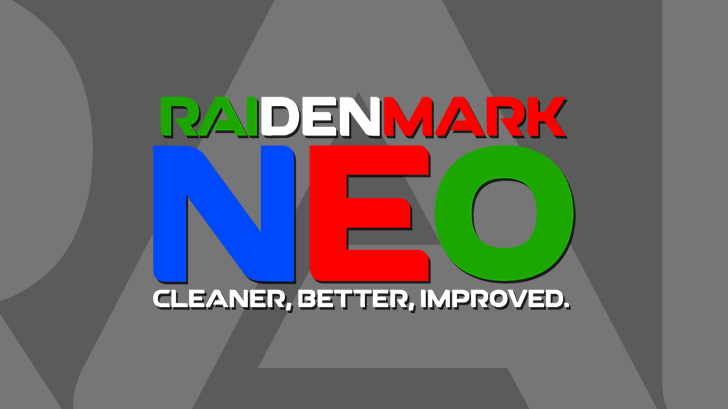
A fonte ‘RAI Denmark Neo’ é uma escolha perfeita para quem busca um estilo clean e moderno para seus projetos digitais no Brasil. Desenvolvida em 2015 por Thomas Kong Database, a font foi inspirada pela tipografia original de 629Lyric. O designer mais conhecido como TK94732 adaptou e modificou esta base, resultando num resultado único que combina elegância com simplicidade. Sua linha clara e sua forma uniforme permitem uma fácil legibilidade em qualquer tamanho, sejam grandes headlines ou detalhes finos de texto. Perfeita para criações gráficas contemporâneas, como sites, aplicativos e logotipos, a ‘RAI Denmark Neo’ oferece um visual moderno que se adapta perfeitamente ao ambiente tecnológico vibrante do Brasil.